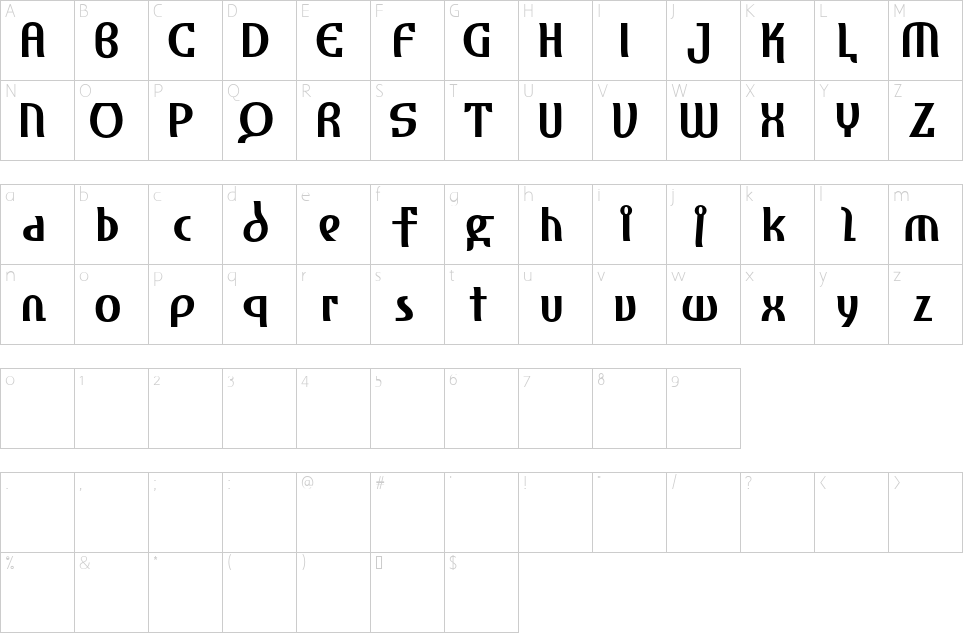
A fonte Amhara é uma elegante escolha para qualquer projeto em busca de uma mistura única e vibrante de estilos. Criada pelo designer Ingo Zimmermann, a Amhara oferece uma combinação sofisticada de linhas curvas e retas, criando um efeito de dinamismo e profundidade em qualquer texto. Esta fonte é especialmente adequada para o design de sites, aplicativos móveis, materiais gráficos e qualquer projeto que busque agregar um toque único e único. Ela tem sido amplamente adotada por designers devido à sua versatilidade e facilidade de uso, tendo sido baixada mais de 22,248 vezes. Se você está procurando uma fonte que não só se destaca, mas também oferece um toque de originalidade à sua marca, a Amhara é uma escolha certeira. Descubra por si mesmo a essência única e vibrante dessa fonte.